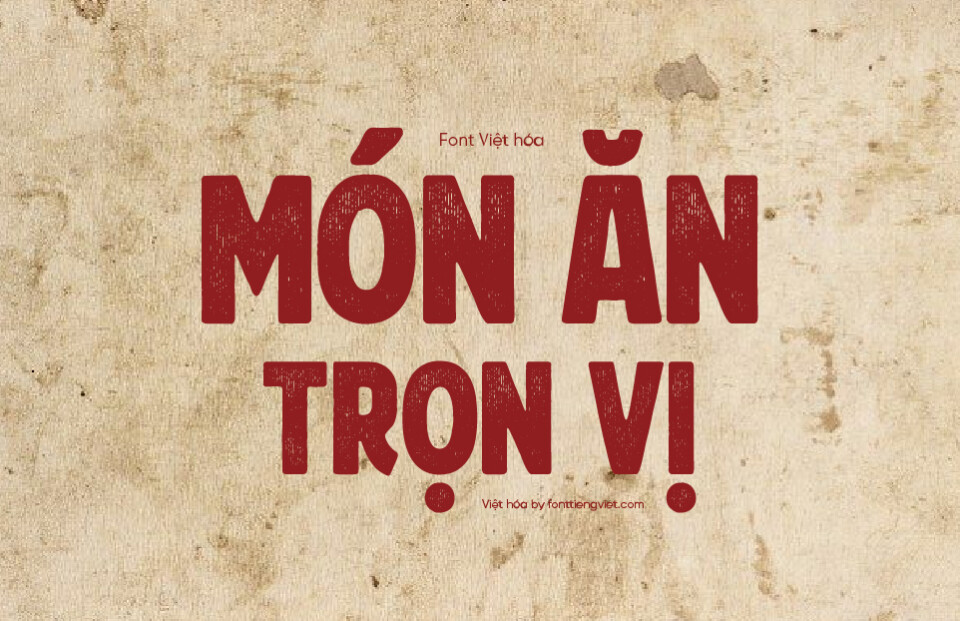
Font Việt hóa 1FTV VIP Rushford Printed
Giới thiệu về Font Việt hóa 1FTV VIP Rushford Printed
Trong thế giới đồ họa hiện đại, việc lựa chọn Font Miễn Phí chất lượng đóng vai trò then chốt giúp các bạn học sinh và giáo viên tạo ra những bài giảng ấn tượng. Font Việt hóa 1FTV VIP Rushford Printed là một bộ phông chữ độc đáo, mang phong cách cổ điển với hiệu ứng in ấn đặc trưng. Điểm nổi bật của bộ font này chính là các đường nét thô mộc, tạo cảm giác gần gũi và chân thực cho người xem.
Tại sao nên sử dụng Font Việt hóa 1FTV VIP Rushford Printed?
Bộ font này được thiết kế để phục vụ các dự án đòi hỏi tính thẩm mỹ cao và sự sáng tạo không giới hạn. Với Font Việt hóa 1FTV VIP Rushford Printed, người dùng có thể dễ dàng ứng dụng vào việc thiết kế bìa sách, làm poster sự kiện trường học hoặc trang trí bảng tin lớp học. Sự kết hợp giữa phong cách Vintage và các ký tự tiếng Việt chuẩn giúp văn bản trở nên chuyên nghiệp và dễ đọc hơn bao giờ hết.
Đặc điểm nổi bật của Font Việt hóa 1FTV VIP Rushford Printed
Phong cách thiết kế và tính ứng dụng
Font Việt hóa 1FTV VIP Rushford Printed sở hữu các chi tiết mô phỏng vết mực in cũ, giúp tạo điểm nhấn mạnh mẽ cho tiêu đề bài viết. Các bạn sinh viên có thể sử dụng font này để làm CV hoặc trình bày bài thuyết trình để ghi điểm trong mắt giảng viên. Đây là lựa chọn lý tưởng cho những ai yêu thích sự phá cách nhưng vẫn giữ được nét thanh lịch cần thiết.